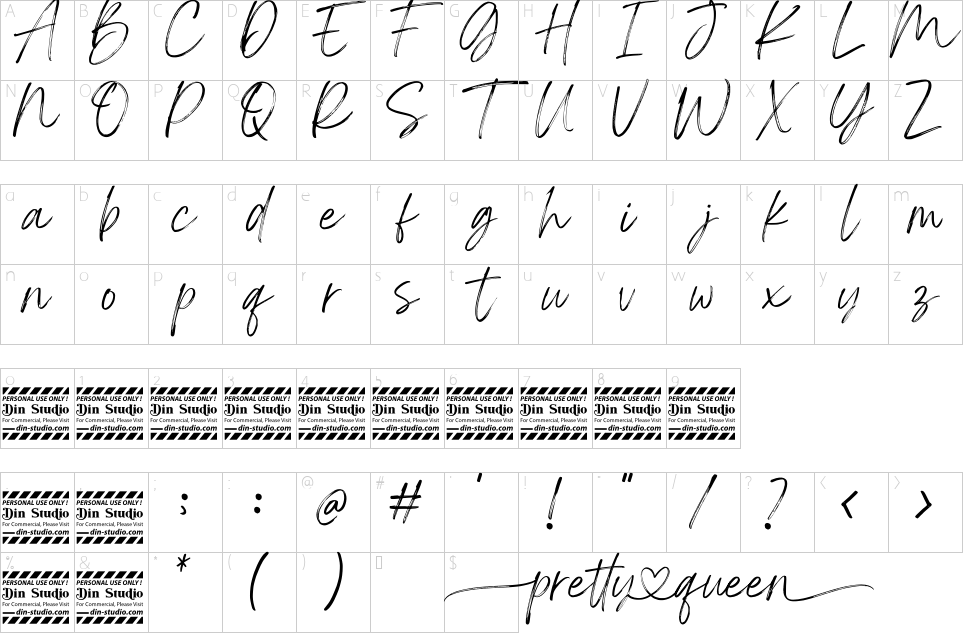
A fonte Pretty Queen é um encantador adorno para qualquer design. Desenhada pelo Din Studio, ela se destacou através de sua elegância e delicadeza. Seu design perfeito para nomes femininos ou qualquer outro tipo de texto que busque um toque de sofisticação. Esta fonte, disponível para Windows e Mac, foi baixada mais de 2.970 vezes, indicando seu valor como um recurso gráfico não menos que encantador. É uma escolha perfeita para designers, grafistas e qualquer um que adora adicionar um toque de romance à sua obra de arte digital.